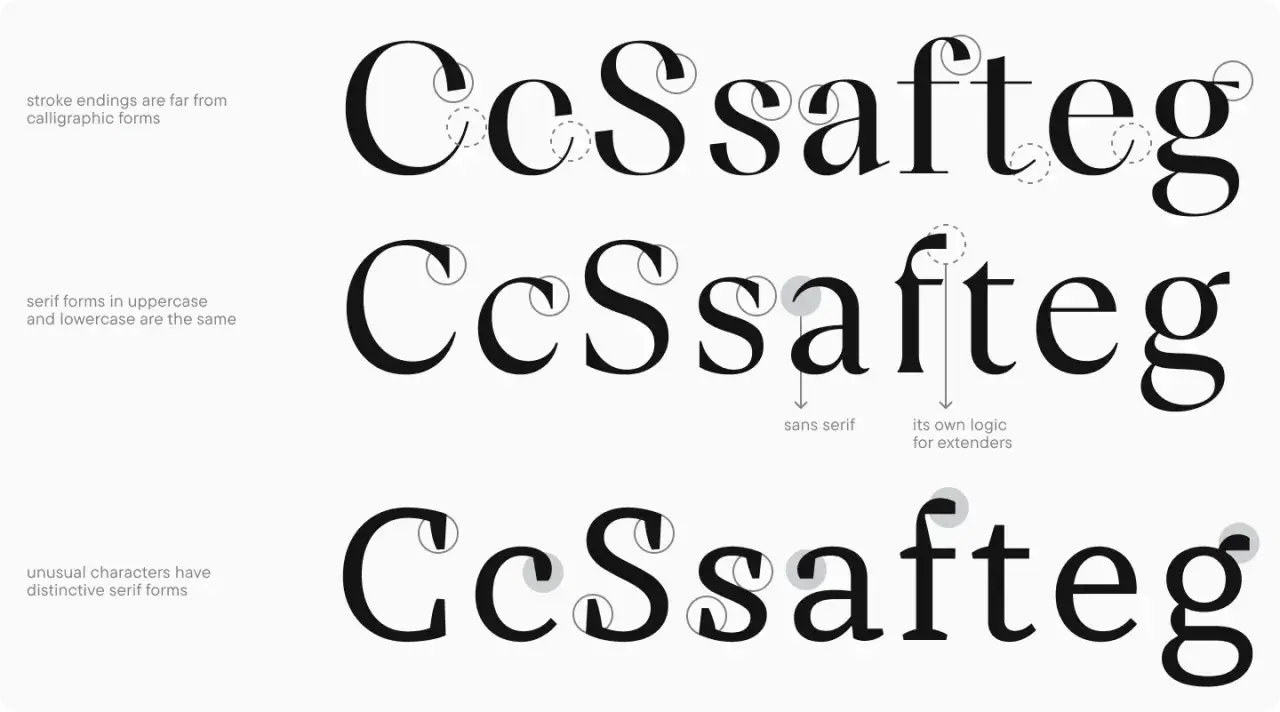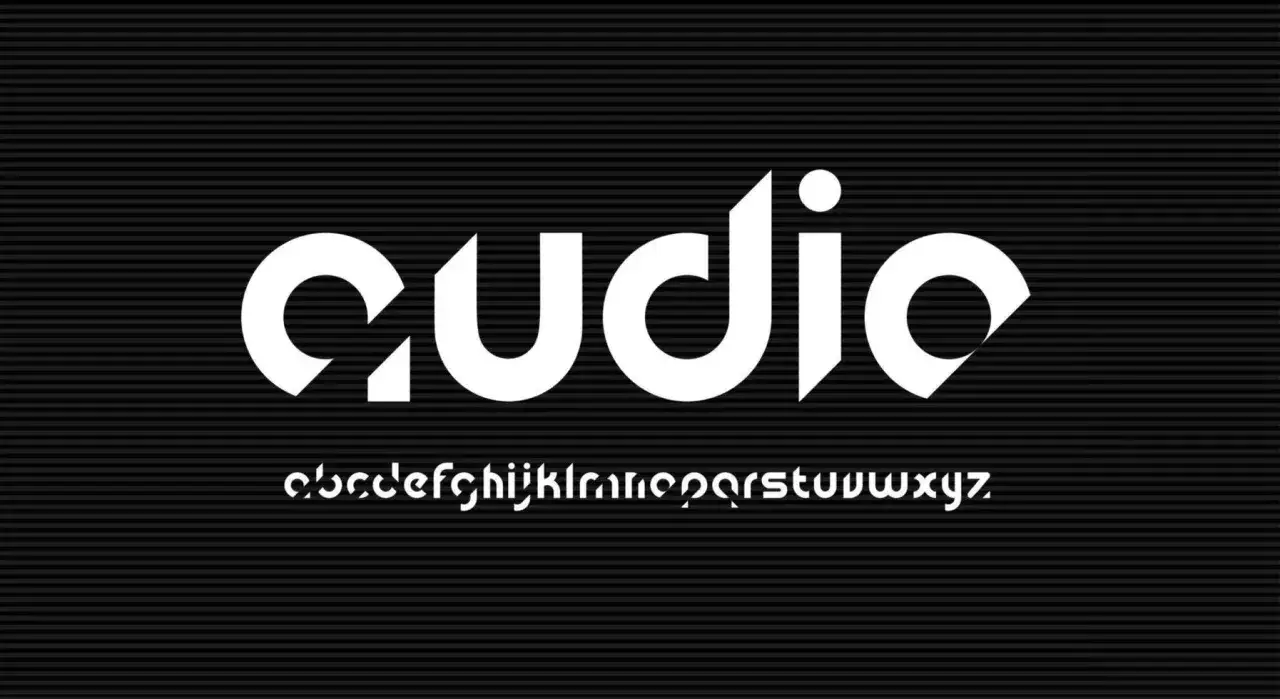
La d minúscula en tipografía - cómo entenderla de un vistazo
Tipografía con remates distintivos. La "d minúscula" y otras letras muestran variaciones en sus remates, con algunas líneas sin serifa.
La d minúscula parece una letra sencilla, pero en tipografía concentra varias decisiones importantes: altura x, contraforma, ritmo y legibilidad. Cuando analizo una familia tipográfica, suelo empezar por esta letra porque delata enseguida si la fuente respira bien o si se ha quedado rígida. Aquí explico cómo reconocerla, cómo cambia entre estilos y qué conviene vigilar cuando la dibujas, la escribes o la usas en un proyecto visual.
Lo esencial para reconocer y usar bien la d minúscula
• La d minúscula combina un asta ascendente con un cuerpo redondeado, y esa mezcla define buena parte de su carácter.
• Su legibilidad depende mucho de la altura x, la contraforma y el espaciado con las letras vecinas.
• En serif, sans serif, cursiva y lettering cambia la proporción, el contraste y la sensación final.
• En tamaños pequeños, una contraforma demasiado cerrada suele ser el primer problema visible.
• Para diseño editorial y branding, conviene probarla siempre dentro de palabras reales, no solo aislada.
Qué revela la d minúscula sobre una tipografía
La d minúscula es una especie de termómetro visual. Tiene una parte vertical, el asta ascendente, que es el trazo que supera la altura x, y una parte curva que llena el cuerpo de la letra. Esa combinación hace que sea muy útil para juzgar si una fuente está bien proporcionada o si alguno de sus trazos se ha quedado forzado.
Yo me fijo sobre todo en cuatro elementos. La altura x es la referencia que marca el cuerpo de las minúsculas sin contar ascendentes ni descendentes; la contraforma es el vacío interior que permite respirar a la letra; la panza o cuerpo redondeado es lo que le da peso visual; y el asta ascendente marca el ritmo vertical de la palabra. Cuando una de esas piezas falla, la d se nota enseguida, incluso antes de leer el texto completo.
• Asta ascendente: da verticalidad y ayuda a ordenar la línea de lectura.
• Altura x: define cuánto “cuerpo” tiene la minúscula y afecta a la legibilidad general.
• Contraforma: si se cierra demasiado, la letra se vuelve pesada y se ensucia.
• Panza o cuerpo redondeado: aporta personalidad y evita que la forma resulte mecánica.
Cuando esos cuatro elementos están equilibrados, la letra funciona casi sin esfuerzo; cuando no, el problema se contagia a toda la palabra. Por eso vale la pena ver cómo cambia según la familia tipográfica, que es justo lo que viene ahora.
Cómo cambia según la familia tipográfica
No todas las d se leen igual. En una serif clásica, la letra suele tener más contraste entre trazos y un gesto más formal; en una sans serif, la forma se limpia y se vuelve más directa; en una cursiva o script, el trazo se integra con el movimiento manuscrito; y en una display o experimental, la letra puede deformarse para ganar personalidad. Esa diferencia no es solo estética: cambia cómo percibe el lector el tono del mensaje.
Familia tipográfica Cómo suele verse la d Ventaja principal Riesgo habitual
Serif Más contraste, remates y una presencia clásica Funciona muy bien en textos editoriales y proyectos formales Puede cerrarse demasiado en cuerpos pequeños
Sans serif Contorno limpio, menos ornamento y lectura rápida Aporta claridad en pantalla, señalética e identidad contemporánea Si la proporción es demasiado neutra, pierde carácter
Script o cursiva Trazo fluido, gesto manuscrito y salida enlazada Da cercanía y movimiento Baja la legibilidad si se usa en exceso o a tamaños pequeños
Display o experimental Proporciones libres, terminales abiertos o formas alteradas Aporta una identidad muy marcada No suele ser buena candidata para párrafos largos
En la práctica, yo no elijo una d por su rareza, sino por su capacidad de sostener el texto. Cuando ya ves esas diferencias, el siguiente paso es más manual: aprender a trazarla sin romper su equilibrio.
Cómo escribirla o dibujarla sin perder la forma
Cuando trabajo una letra a mano, separo siempre tres contextos: imprenta, cursiva y lettering. No conviene tratar la d como si todos los sistemas pidieran el mismo gesto, porque el problema casi siempre aparece cuando se copia una lógica de un estilo a otro sin adaptarla.
En imprenta
En imprenta, la d suele construirse a partir de una base sencilla: un asta recta y un cuerpo redondeado que se apoya sobre la línea base. Yo lo pienso como dos decisiones: primero la estructura, después la masa. Si el asta es demasiado corta, la letra parece encogida; si la parte redondeada se cierra demasiado, el interior pierde aire.
1. Traza un asta estable y limpia, sin oscilaciones.
2. Construye el cuerpo redondeado con una curva que respete la proporción general.
3. Deja una contraforma suficientemente abierta para que la letra no se empaste.